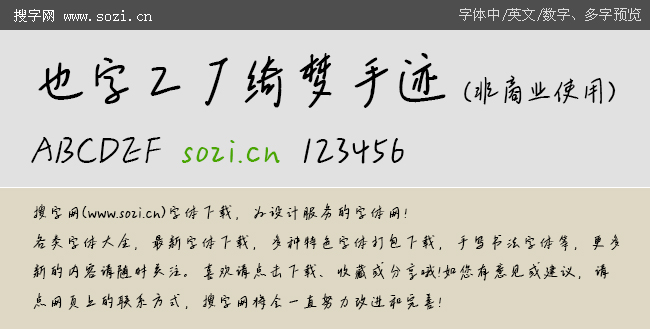
也字工廠綺夢手跡
搜字網(wǎng)給大家提供一款也字工廠綺夢手跡(非商業(yè)使用)中文字體下載,也字工廠綺夢手跡是一款手寫書法字體,字體書寫流暢,自然大方,具有很好的視覺效果。適合應(yīng)用于書籍畫冊、海報、網(wǎng)頁設(shè)計等應(yīng)用(此字體為個人非商用版,商用可以聯(lián)系:官方網(wǎng)址:https://yefont.com/home,聯(lián)系方式:13798980448)。